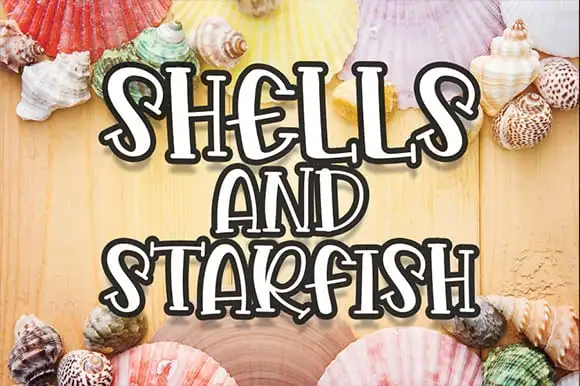
Shells And Starfish Display Font – Download Grátis
A fonte Shells And Starfish Display Font é uma obra-prima perfeita para os estilos decorativos que enriquecem seu projeto com sofisticação e originalidade. Inspirada nas formas geométricas e na elegância dos elementos marinhos, essa fonte oferece um toque único em qualquer aplicação visual. Suas curvas delicadas e suas formas simples são perfeitas para criações de ambientes decorativos como displays e paredes, ou para personalizar invitations de casamento, postagens no Instagram com logotipos, e até mesmo etiquetas de produtos. Ideal para atrações digitais e físicas, essa fonte também se destaca em logos de publicidade, embalagens de produtos, capas de livros, gráficos e até mesmo como fundo de água da imagem. Seja qual seja seu projeto, Shells And Starfish Display Font certamente acrescentará um toque especial e único.